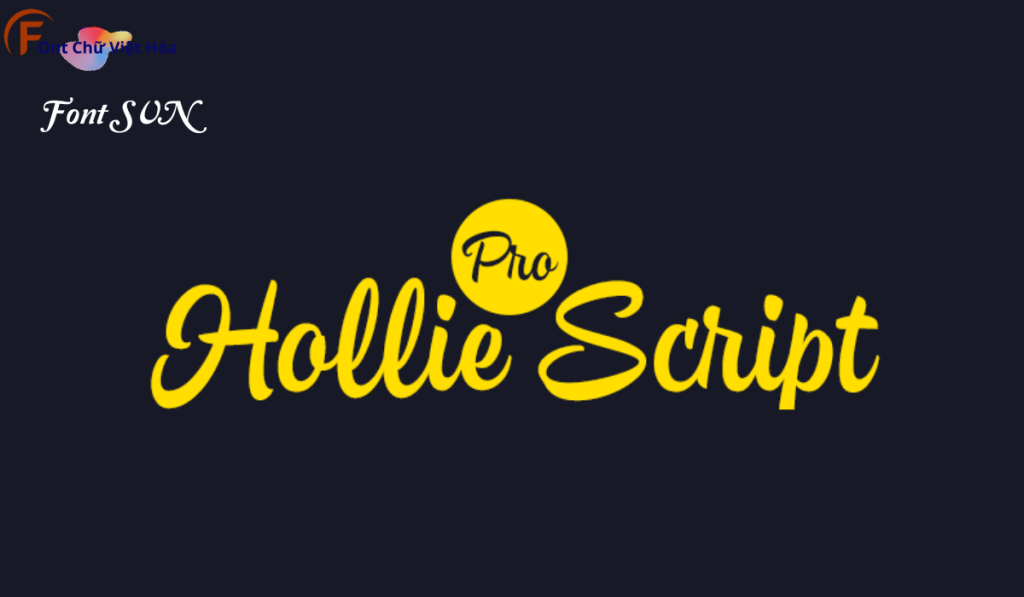
Font SVN – Hoddie Script Việt Hóa
Font SVN-Hoddie Script Việt Hóa
Phân loại: Cá tính, Lãng mạn
Kiểu chữ: Chữ viết tay
Font SVN-Hoddie Script Việt Hóa là một font chữ viết tay cá tính, thuộc bộ font SVN. Được thiết kế với mục tiêu mang lại sự mềm mại và thanh thoát, font này lý tưởng cho các dự án thiết kế như thiệp mời, logo, và bao bì sản phẩm. Với các nét chữ uyển chuyển và độ dày đều đặn, Font SVN-Hoddie Script Việt Hóa không chỉ dễ đọc mà còn tạo cảm giác thân thiện và gần gũi. Việc Việt hóa font giúp người dùng dễ dàng sử dụng trong các thiết kế tiếng Việt, mang lại sự tiện lợi và thẩm mỹ cao.